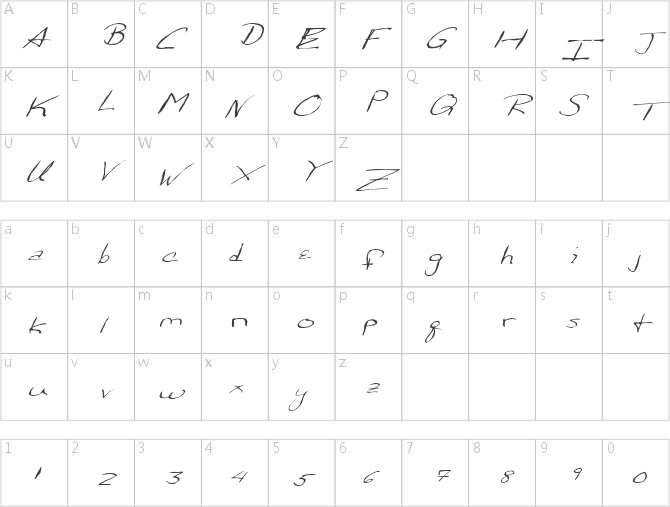
FZ HAND 24 MANGLED ITALIC
FZ HAND 24 MANGLED ITALIC介紹
FZ HAND 24 MANGLED ITALIC字體字庫是一款讓人賞心悅目、百看不厭的英文字體,適合各類廣告和產品包裝設計應用,字體大小0.06MB,格式為ttf字體,上傳用戶是woslxn,作者/版權方為未知
FZ HAND 24 MANGLED ITALIC效果圖